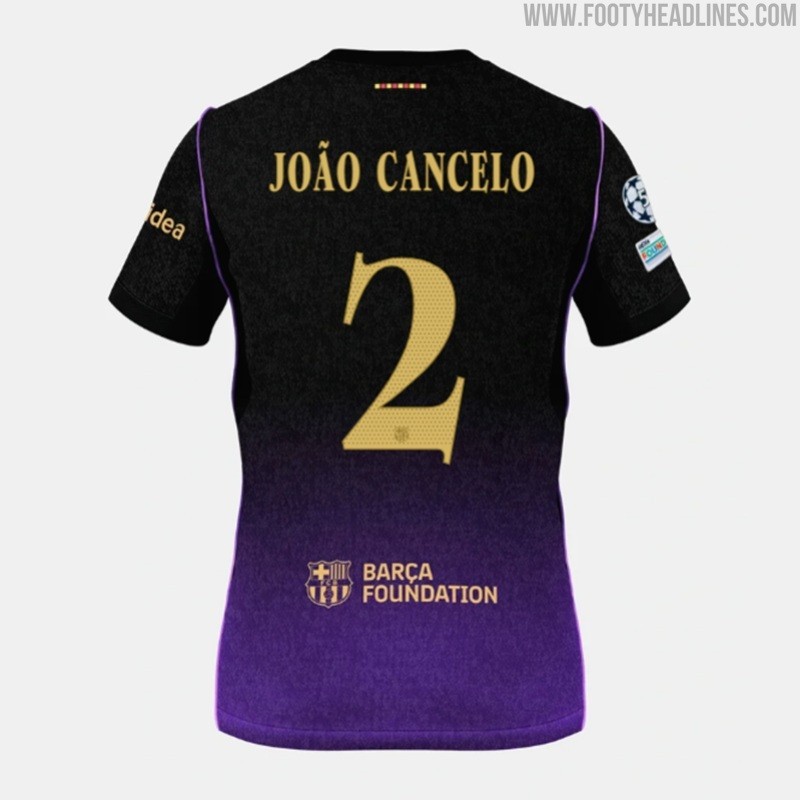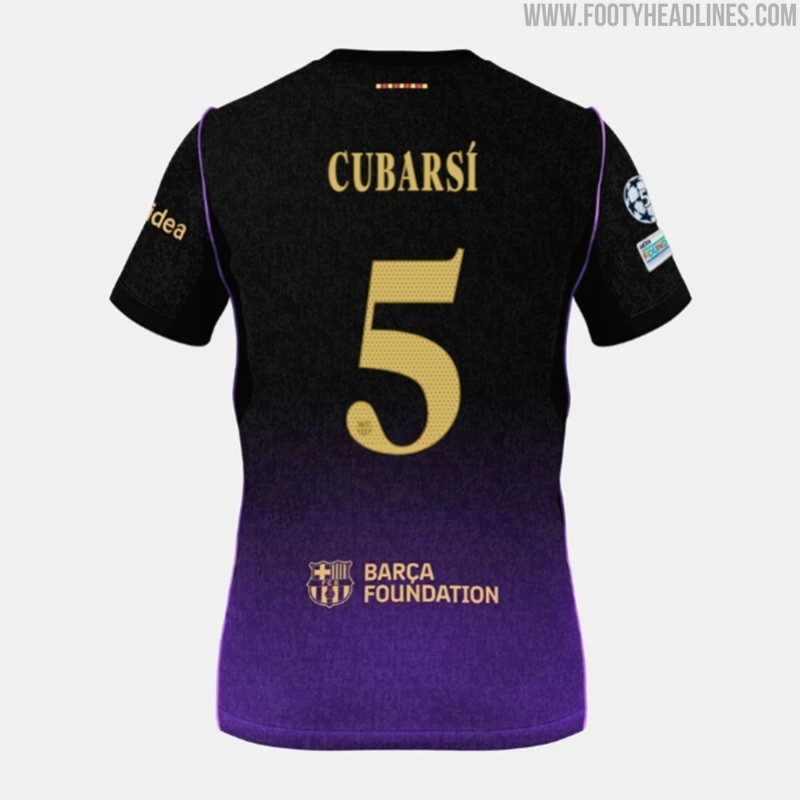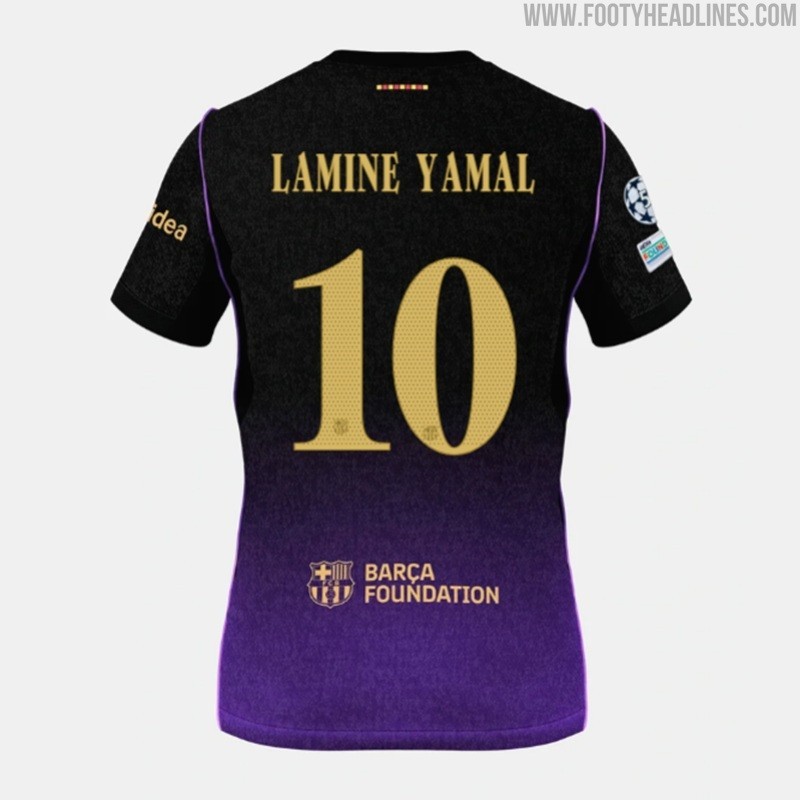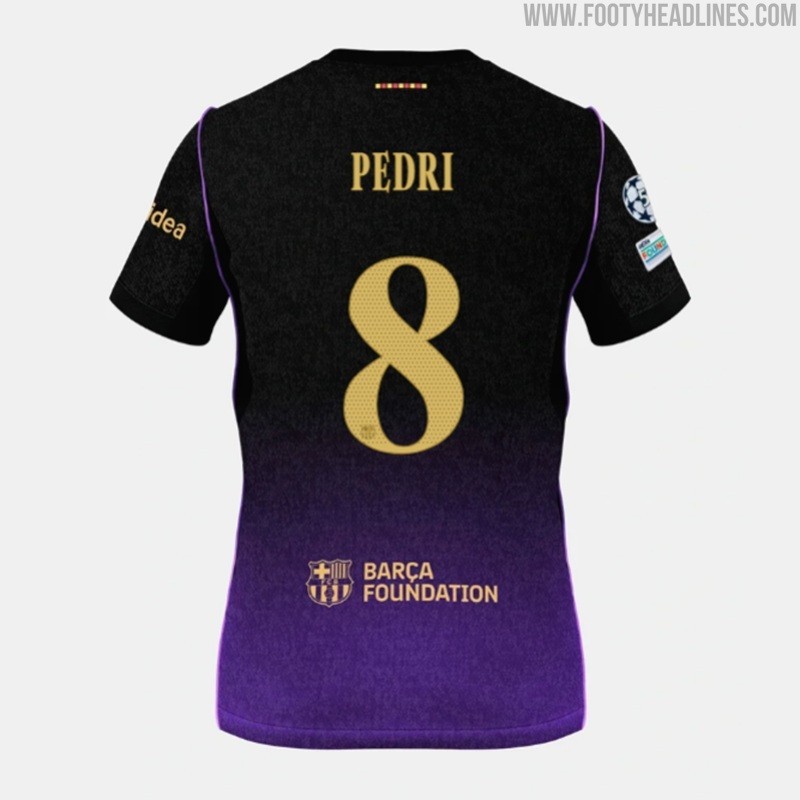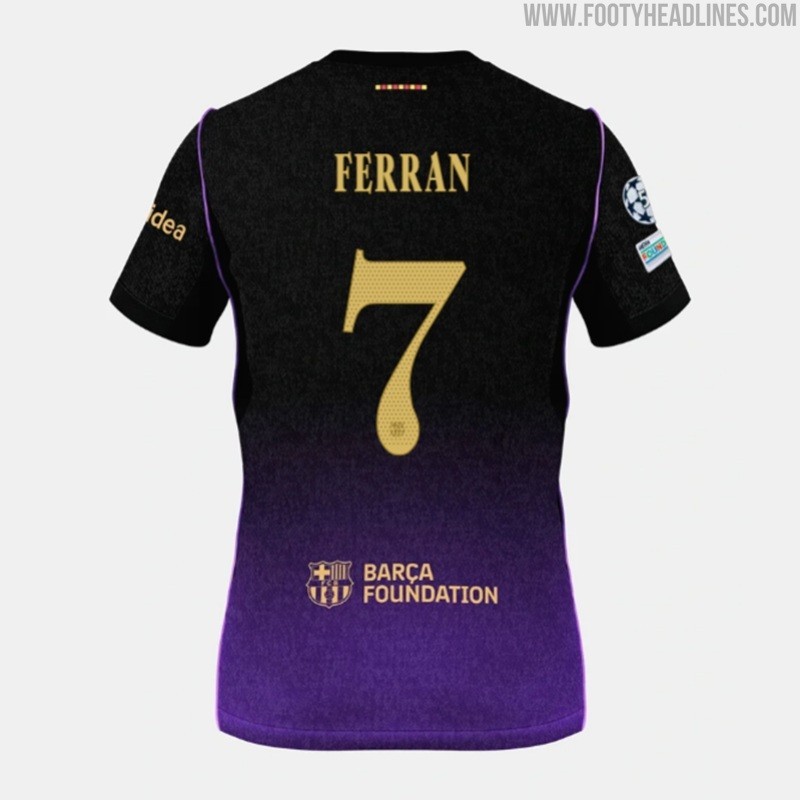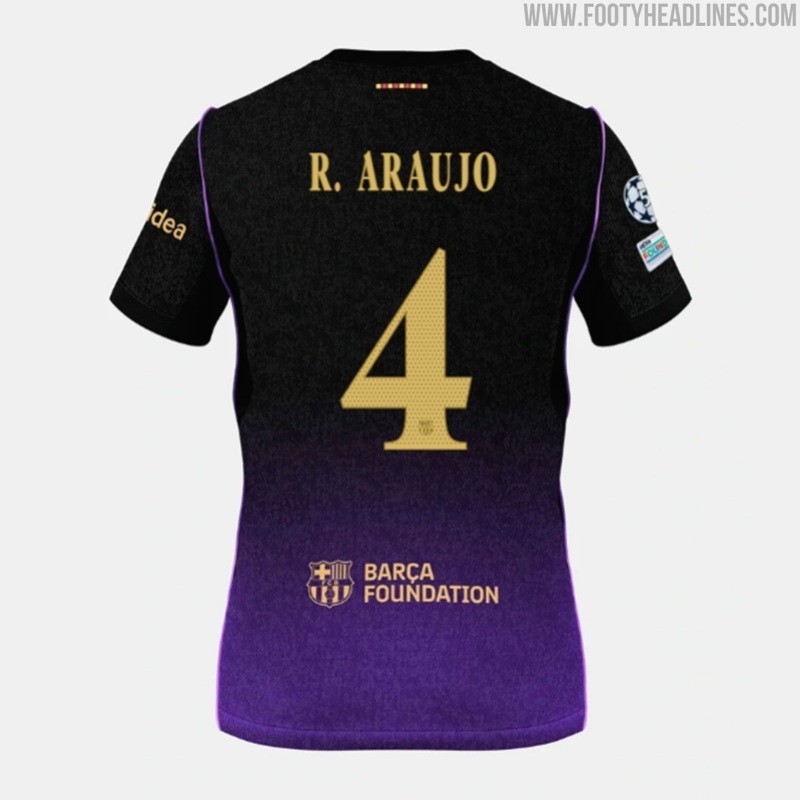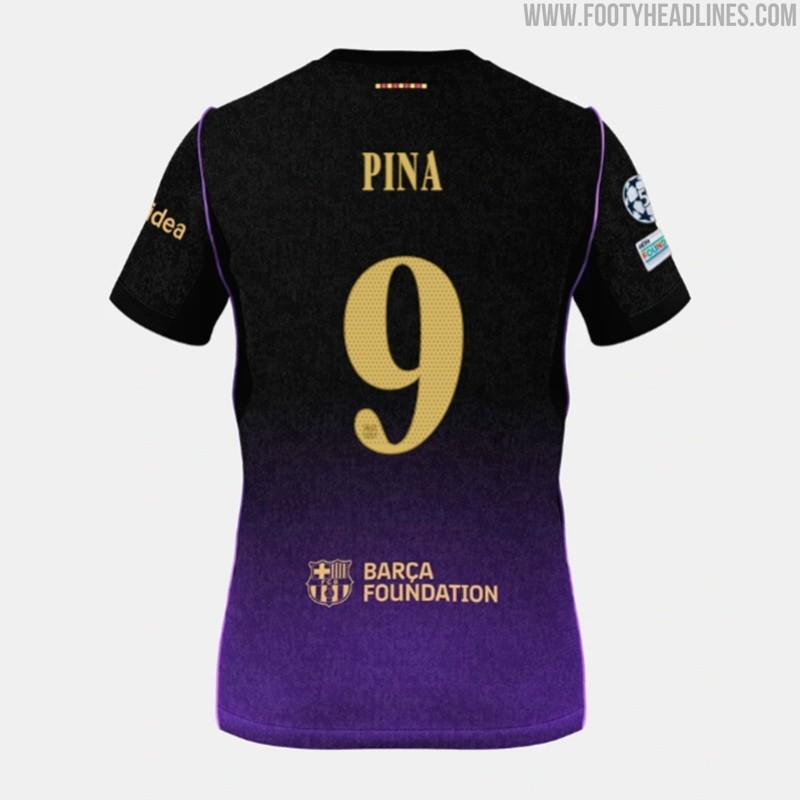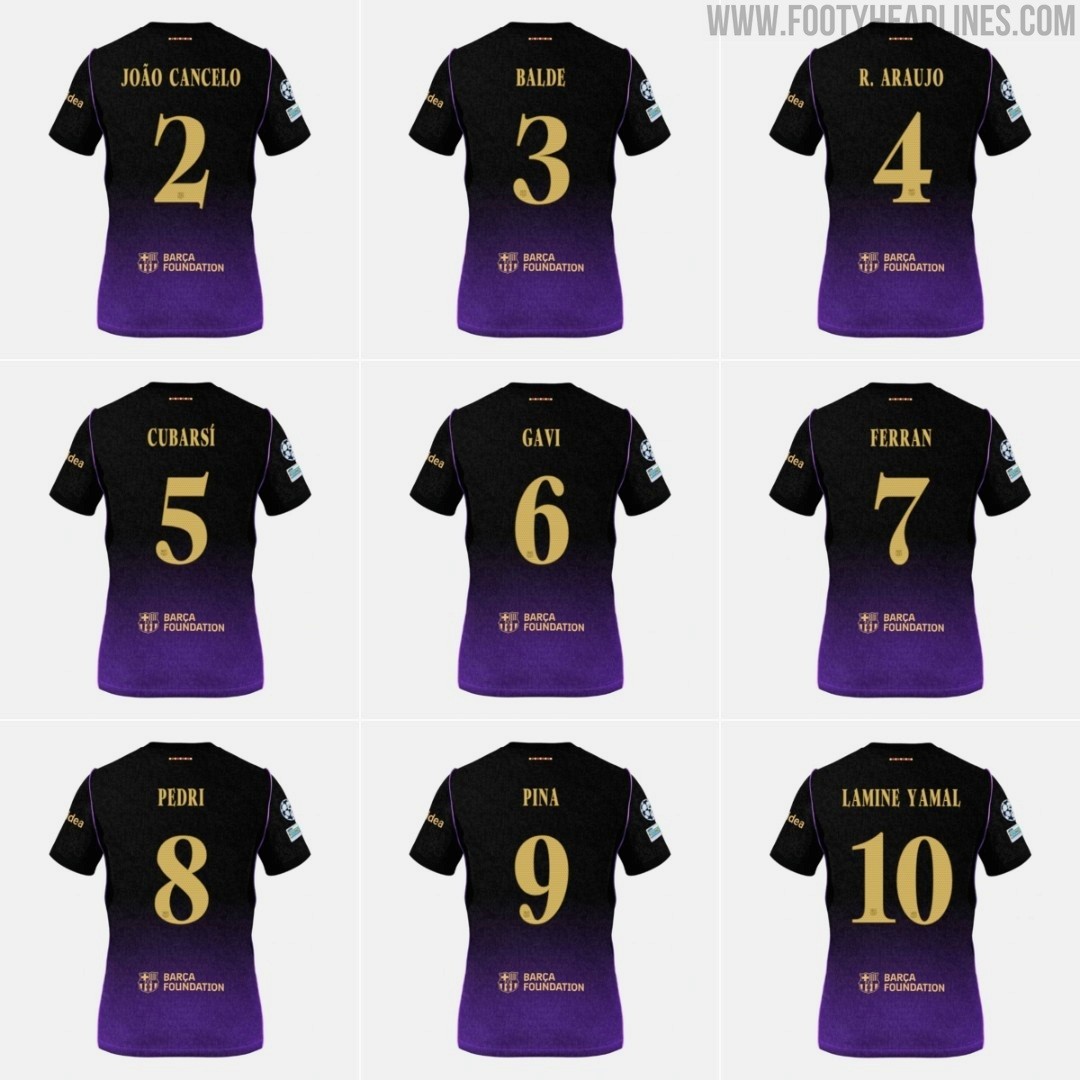
Die brandneue Schriftart für das Auswärtstrikot „Gold Mamba“ des FC Barcelona 26–27 ist erschienen
• Neue exklusive Schriftart: Der FC Barcelona hat eine brandneue, exklusive Schriftart für sein Auswärtstrikot der Saison 2026–2027 vorgestellt, die sich von der Heimtrikot-Typografie unterscheidet.
• Design und Farbe: Die neue Schriftart präsentiert sich in einem satten, metallischen Goldton mit eleganten Serifenbuchstaben und raffinierten Verzierungen, die dem Trikot einen luxuriösen Look verleihen.
Zusammen mit der offiziellen Vorstellung ihres neuen Auswärtstrikots hat der FC Barcelona eine brandneue, speziell für das Auswärtstrikot der Saison 2026–2027 entwickelte Schriftart präsentiert. Anders als in den vergangenen Spielzeiten ist diese neue Schriftart exklusiv für das Auswärtstrikot bestimmt und unterscheidet sich vollständig von der Typografie, die auf dem Trikot verwendet wird.
Schriftart des FC Barcelona Auswärtstrikots 26-27
Schau dir unten die brandneue Schriftart für das Auswärtstrikot des FC Barcelona 2026–2027 an.
Die neue Schriftart des FC Barcelona Auswärtstrikots 26-27 präsentiert sich in einem satten, metallischen Goldton. Dieser leuchtende Goldfarbton bildet einen starken Kontrast zum dunklen schwarz-lila Hintergrund des Trikots und passt perfekt zu den goldenen Ärmelbündchen, den Sponsorenlogos und dem Vereinswappen auf der Vorderseite.
Die neue Auswärts-Schriftart des FC Barcelona für die Saison 26/27 wirkt edel, luxuriös und raffiniert. Eine Eigenschaft der Typografie ist die Verwendung eleganter Serifenbuchstaben mit raffinierten Verzierungen sowohl bei den Buchstaben als auch bei den Zahlen, was den Spielernamen einen hochwertigen, hochmodischen Look verleiht.